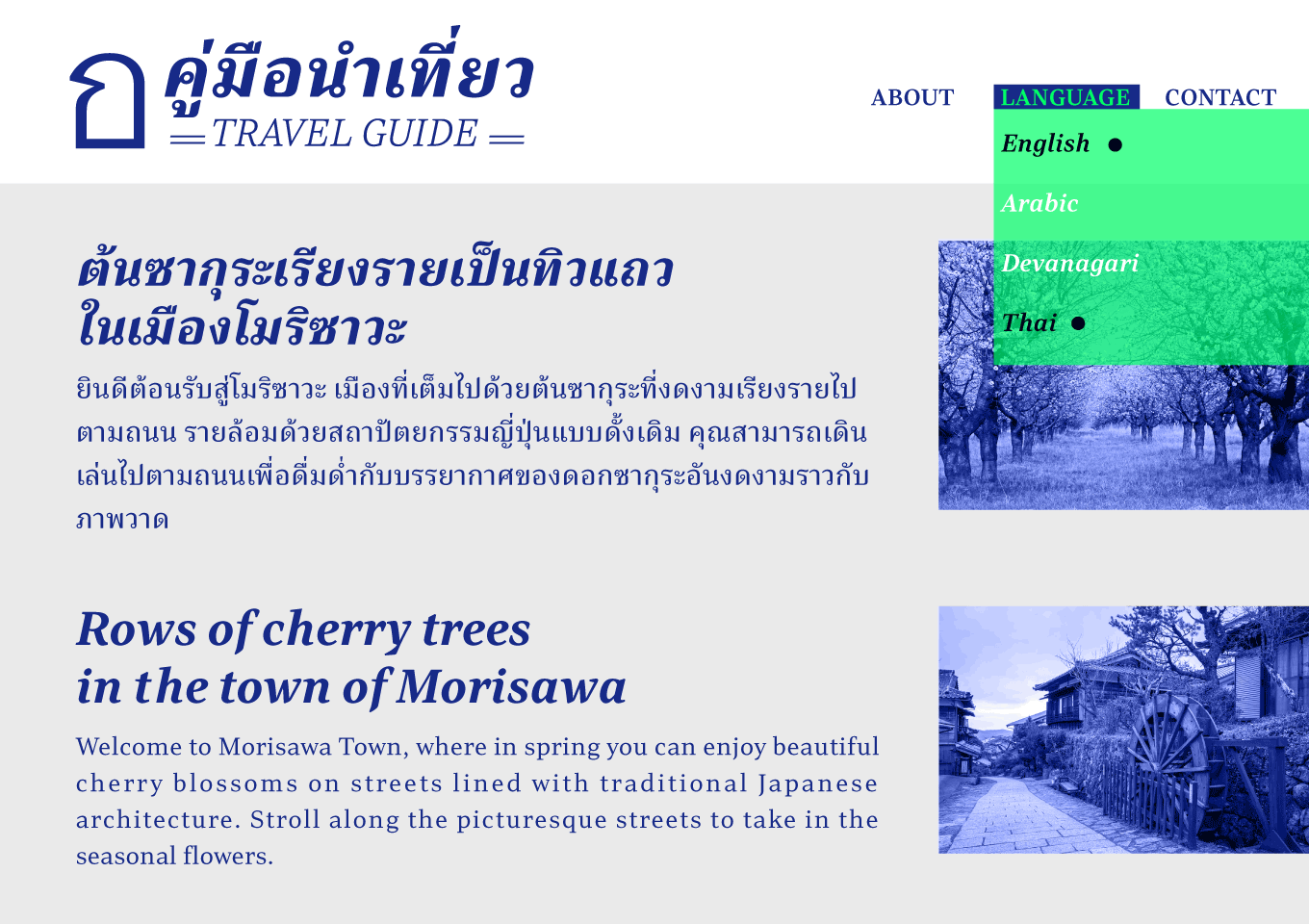
「Lutes UD Thai」は欧文フォント 「Lutes UD PE」の多言語展開として作成されたタイ文字のフォントです。デジタルデバイス上での視認性に配慮した、ローコントラストでありながらもクリアですっきりとした印象のセリフ書体「Lutes UD PE」の特徴を反映しています。伝統的なスタイルであるループ有りのタイ文字で作成しつつも近代的な印象を与えることができます。